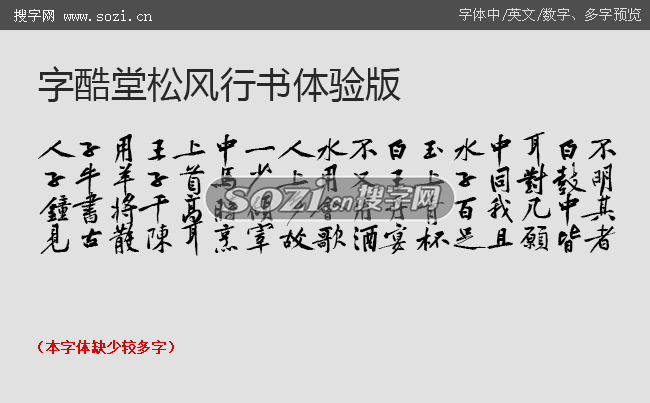
字酷堂松風(fēng)行書體驗(yàn)版
搜字網(wǎng)提供一款字酷堂松風(fēng)行書體驗(yàn)版手寫中文書法字體下載,字酷堂松風(fēng)行書體驗(yàn)版是一款非常漂亮的手寫字體,字體極具藝術(shù)風(fēng)格,每筆每畫都給人一種飄逸灑脫的感覺,整體效果非常出色,能夠應(yīng)用于平面設(shè)計(jì)、名片設(shè)計(jì)、廣告創(chuàng)意、印刷等場合應(yīng)用。